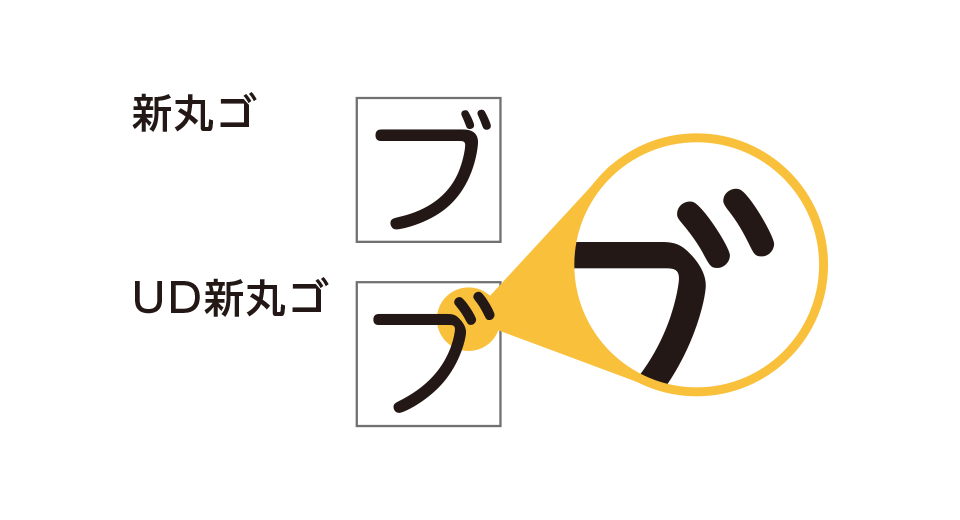
「MORISAWA BIZ+」は、保険営業の現場のあらゆるドキュメントやコンテンツの作成に、多くの人々が利用しやすいユニバーサルデザイン(UD)フォントの利用を提案する新しいサービスです。
文字のかたちが
わかりやすい
文字サイズが小さくても読みやすい
読みまちがえにくい
Office アプリケーションに最適化
読みやすいフォントだから
正しく伝えることを
サポートします。
もしも提案資料や約款の文字が読みにくかったら・・・?
3が8に見えてしまう、濁点と半濁点の判別ができない。
細い文字がかすれて読めない・・・。
書類の文字の不明瞭さは、あなたの仕事の上で致命的なミスを引き起こしてしまうかもしれません。お客様の大切な資産を預かる仕事だからこそ、文字の形がわかりやすく、読みやすく、読み間違えにくいフォントで大切な情報を正しく伝えることをサポートします。
UDフォントで
コミュニケーションが
もっと快適に
せっかく説明した提案書も、お客様が読み返されなければ機会損失につながります。日常的に作成する書類や掲示物などをもっと見やすくしたい、「MORISAWA BIZ+」は、見やすくて分かりやすいフォントだから、伝えたい情報が正しく伝わります。
UDフォントで
保険業界業界のユニバーサルデザインを実現
人は情報の80%以上を視覚から得ていると言われています。そして、その視覚情報のほとんどは、文字によってもたらされていることは、もはや疑いのないことでしょう。
近年多くの公共機関で導入されているユニバーサルデザイン。「MORISAWA BIZ+」は、ユニバーサルデザイン(UD)に対応したフォントです。年齢や性別などにかかわらず、多くの人々が見やすいフォントであなたが伝えたい相手の理解と満足度の向上に繋がります。
※「MORISAWA BIZ+」は、一般財団法人 国際ユニヴァーサルデザイン協議会が主催する「IAUDアウォード2017」で銀賞を受賞しています。
モリサワのUDフォントは
既にさまざまな場面で活躍しています
手書きの文字を自動判定し、小学生で習う漢字を学年を超えて正しい書き順・形で「書く力」を育むアプリです。小学1・2年生の漢字で採用されています。
孔子の言葉にドラえもんのイラストが付いた小学生向きオールカラー論語入門書です。孔子の言葉部分に「UDデジタル教科書体」が採用されています。
モリサワのUDフォントはユーザー評価に基づく
読みやすさのエビデンスを取得しています。
ロービジョンのエビデンス
(UDデジタル教科書体の調査結果)
慶應義塾大学 中野泰志教授による
Aデジタルデバイス(タブレット)での見やすさの検証
縦組み(科目:国語)・横組み(科目:社会)で、UDデジタル教科書体と他社教科書体をタブレット画面で比較し、シェッフェの一対比較法を用いて、それぞれの見やすさを検証した。
いずれの評価においても「UDデジタル教科書体」が最も見やすい書体であった。
B紙に印刷したサンプルでの読みやすさの調査
日本全国の視覚支援学校に在籍している高校生42人へのアンケートとヒアリング調査、弱視教育に携わっている教員・専門家65人へのアンケート調査、全国の視覚支援学校で弱視の生徒を担当している教員104人へのアンケート調査を実施した。
弱視生徒にとっても教員からみても、弱視児童生徒の読書に「UD デジタル教科書体」がもっとも適した書体であった。
ディスレクシアの
エビデンス
(UDデジタル教科書体の調査結果)
大阪医科大学 LDセンター
奥村智人先生による
デジタルデバイス(タブレット)での見やすさの検証
読み書きに困難さがある26人の小学2~6年生を対象に、UDデジタル教科書体を含む4つの教科書体で縦組みと横組みの文章を制作し、一対比較法を用いた主観的読みやすさに関する検討が行われた。
縦組み横組みともに「UDデジタル教科書体」がもっとも読みやすい書体として子どもたちに選択された。
従来のビジネスフォントの比較調査
(BIZ UDゴシック・BIZ UD明朝の調査結果)
デジタルデバイス(タブレット)での見やすさの検証
全国93カ所のハローパソコン教室を対象に、UD書体の比較アンケート調査を実施。BIZ UDフォントと標準的なフォントの「見やすさ」を検証した。
ゴシック体・明朝体ともにBIZ UD フォントがもっとも見やすい書体として選択された。
見やすさの比較
BIZ UD新ゴ・BIZ UD新丸ゴ・BIZ UD黎ミンについて
BIZ UD新ゴ・BIZ UD新丸ゴ・BIZ UD黎ミンは、慶應義塾大学と共同で行った比較研究でその優位性が検証されたモリサワUDフォントをベースに作成されています。「必ず伝えたい情報」「注意を促したい文言」「さりげなく添えたい文章」など、必要な表現に合わせてフォントを変えることが可能となり、情報の「伝わりやすさ」に大きな差がつきます。数字の多い文書や提案資料、公的文書、各種案内など、より多くの人が目にする文書の作成に最適です。